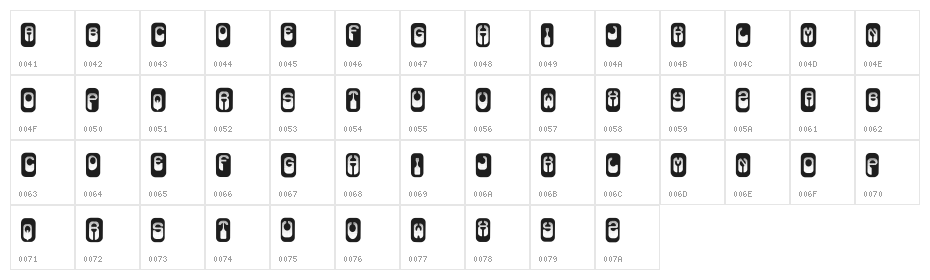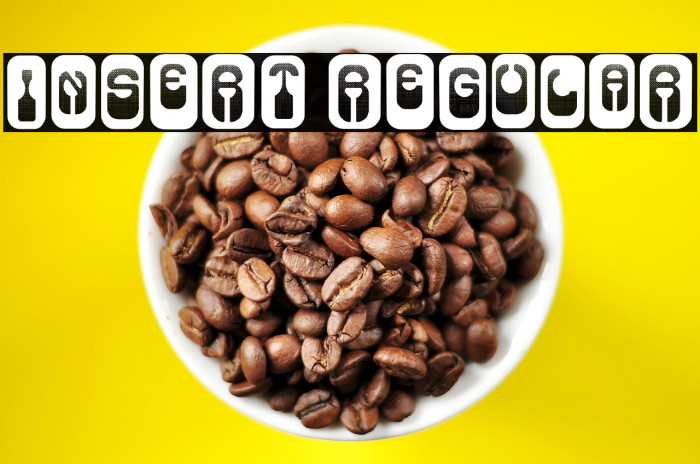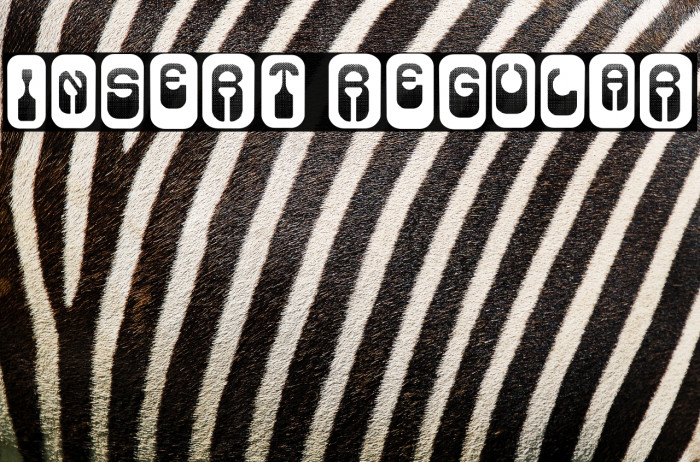
Insert Regular Font
✎ Stencil
| Categorie | Stencil |
| Stile generale | Modern, Industrial |
| Progetti proposti | Ideal for branding, poster design, album covers, and any project needing a bold, modern aesthetic. |